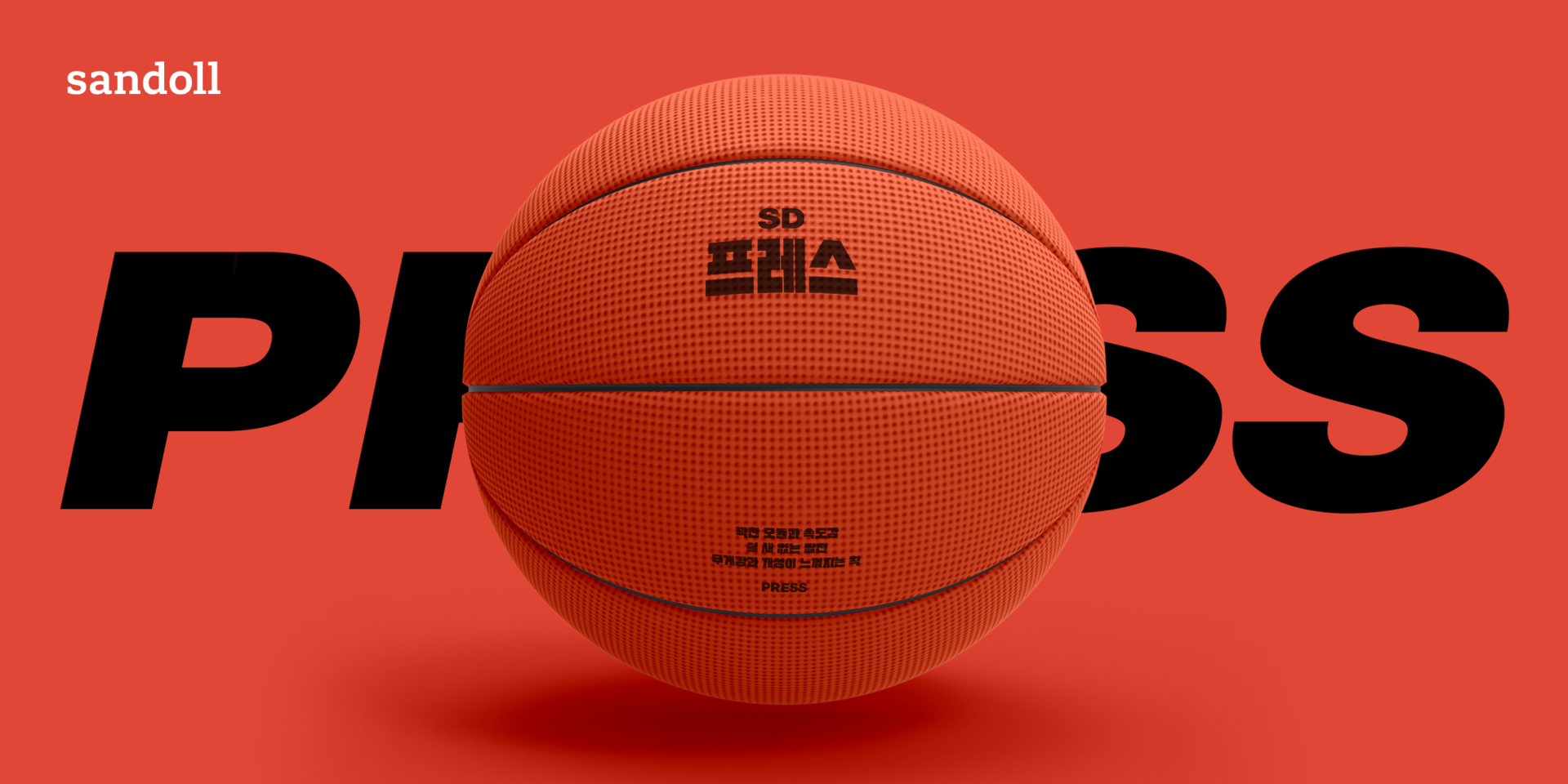
Sandoll 프레스
산돌 프레스는 시대의 거울 프로젝트의 네 번째 결과물로 쉴 새 없이 생산되며 발전하는 대중문화의 속도감을 표현한 폰트이다.무게감이 느껴지는 꽉찬 획과 개성있는 복합모임꼴, 넓고 낮은 모습의 자폭, 그리고 무엇보다 대량생산의 속도감이 느껴지는 기울기가 특징이다.